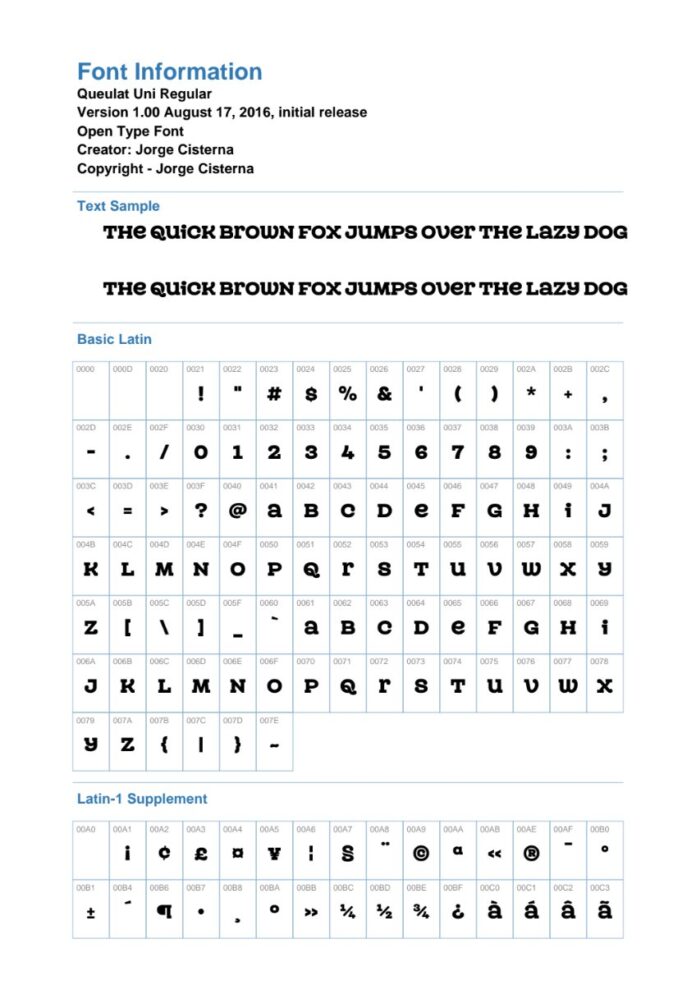
Font Queulat Uni Regular
Font Queulat Uni Regular. Khám phá Font Queulat Uni Regular, một kiểu chữ Open Type độc đáo từ Latinotype. Phù hợp cho thiết kế hiện đại, mang lại sự chuyên nghiệp và sáng tạo cho mọi dự án của bạn. Tải ngay tại Poster.vn!
Queulat Uni Regular: Sự Kết Hợp Hoàn Hảo Giữa Cổ Điển và Hiện Đại
Font Queulat Uni Regular nổi bật với sự kết hợp tinh tế giữa nét cổ điển và phong cách hiện đại. Các ký tự được thiết kế với độ dày vừa phải, mang lại cảm giác mạnh mẽ nhưng vẫn giữ được sự thanh lịch. Điều này làm cho Queulat Uni Regular trở thành một lựa chọn lý tưởng cho các tiêu đề, logo, branding, và các ấn phẩm quảng cáo cần sự chú ý.
Đặc Điểm Nổi Bật Của Font Queulat Uni Regular
• Thiết kế độc đáo: Mỗi ký tự đều được chăm chút tỉ mỉ, tạo nên một tổng thể hài hòa và dễ đọc.
• Tính linh hoạt cao: Phù hợp với nhiều loại hình thiết kế khác nhau, từ in ấn đến kỹ thuật số.
• Hỗ trợ đa ngôn ngữ: Bao gồm các ký tự Latin cơ bản và bổ sung Latin-1, giúp bạn dễ dàng sử dụng trong các dự án đa ngôn ngữ.
• Định dạng Open Type: Đảm bảo khả năng tương thích rộng rãi với các phần mềm thiết kế chuyên nghiệp.
Ứng Dụng Của Font Queulat Uni Regular Trong Thiết Kế
Với Queulat Uni Regular, khả năng sáng tạo của bạn là vô hạn. Dưới đây là một số gợi ý về cách bạn có thể tận dụng font chữ này:
1. Thiết Kế Logo và Branding
Sự độc đáo của Queulat Uni Regular giúp logo và bộ nhận diện thương hiệu của bạn trở nên nổi bật và dễ nhớ. Font chữ này mang lại cảm giác chuyên nghiệp và hiện đại, rất phù hợp cho các công ty công nghệ, thời trang, hoặc các thương hiệu muốn tạo ấn tượng mạnh mẽ.
2. Tiêu Đề và Headline
Các tiêu đề và headline được viết bằng Queulat Uni Regular sẽ thu hút sự chú ý ngay lập tức. Độ rõ nét và phong cách đặc trưng của font chữ này giúp thông điệp của bạn được truyền tải một cách hiệu quả và ấn tượng.
3. Ấn Phẩm Quảng Cáo và Marketing
Từ poster, banner, brochure đến các ấn phẩm kỹ thuật số, Queulat Uni Regular đều có thể làm tăng tính thẩm mỹ và chuyên nghiệp cho tài liệu của bạn. Font chữ này giúp tạo ra một bố cục hấp dẫn và dễ đọc, khuyến khích người xem tương tác với nội dung.
4. Thiết Kế Website và Ứng Dụng
Trong thiết kế giao diện người dùng (UI/UX), Queulat Uni Regular có thể được sử dụng cho các tiêu đề, nút bấm hoặc các yếu tố quan trọng khác để tạo điểm nhấn. Sự rõ ràng và hiện đại của font chữ này sẽ cải thiện trải nghiệm người dùng.
Font Queulat Uni Regular là gì?
Queulat Uni Regular là một kiểu chữ Open Type được thiết kế bởi Jorge Cisterna, thuộc Latinotype, nổi bật với sự kết hợp giữa phong cách cổ điển và hiện đại.